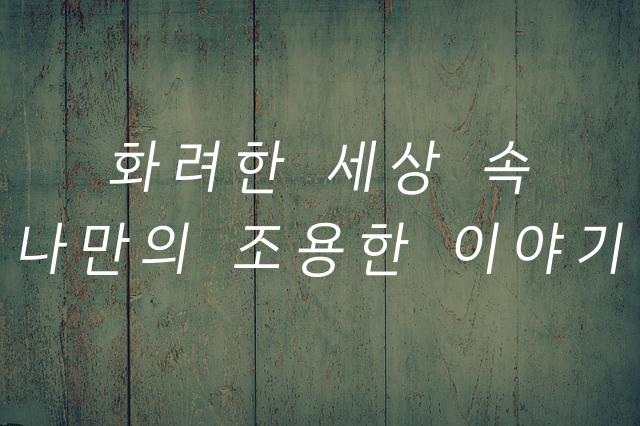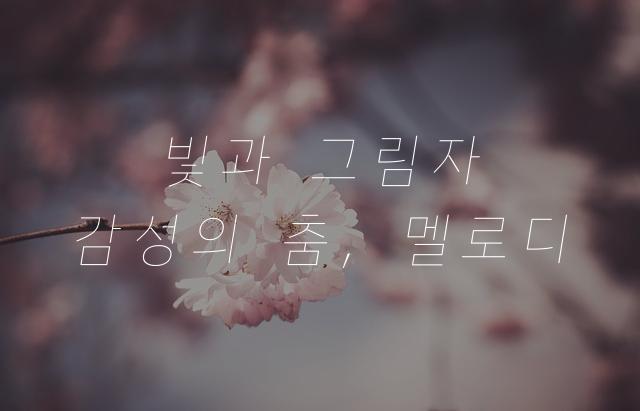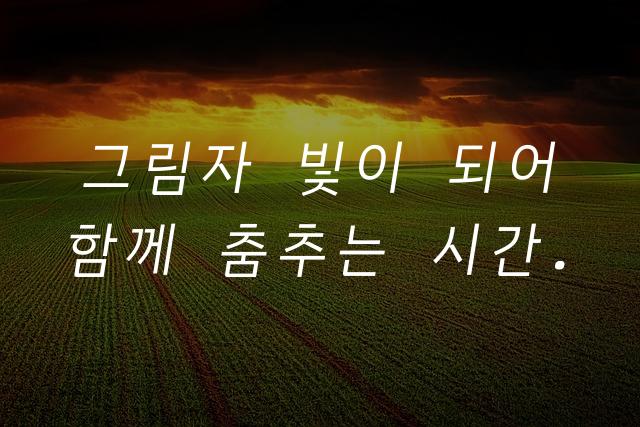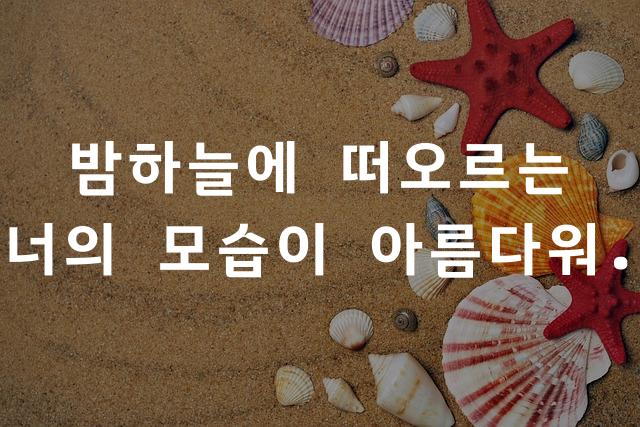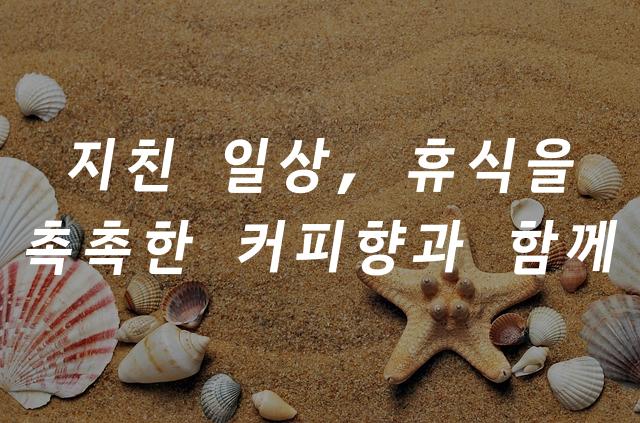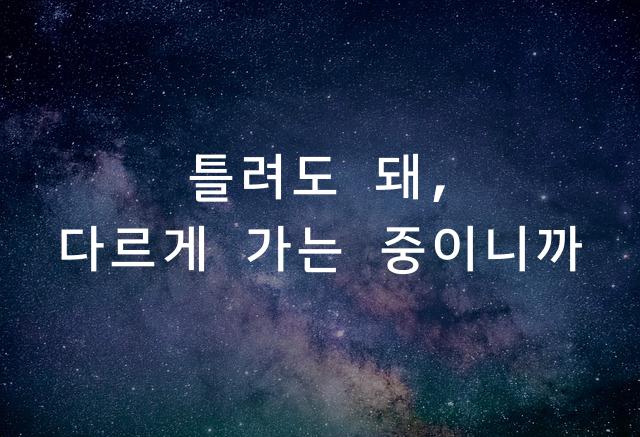
모노플렉스KR은 김양수 제작사에서 만든 문서용 기본 고딕 폰트입니다. 깔끔하고 현대적인 느낌을 주며, 일상적인 문서에서부터 전문적인 보고서에 이르기까지 폭넓게 사용될 수 있습니다.
모노플렉스KR은(는)
기본 고딕, 감성적인, 부드러움 계열의 생김새를 가지고 있으며
광고 캠페인, 웹/앱 디자인, 브랜딩 등에서 자주 활용되며, 효과적인 메시지 전달에 적합합니다.
이 폰트는 광고/마케팅, 크리에이티브, 기술/IT 분야에 잘 어울리며,
세련된, 명확한, 전문적인 느낌을 담고 있는 것이 특징입니다.
이 폰트와 유사한 폰트로는 나눔고딕, 굴림, 돋움 등이 있어요. 함께 비교해 보시면 좋습니다!